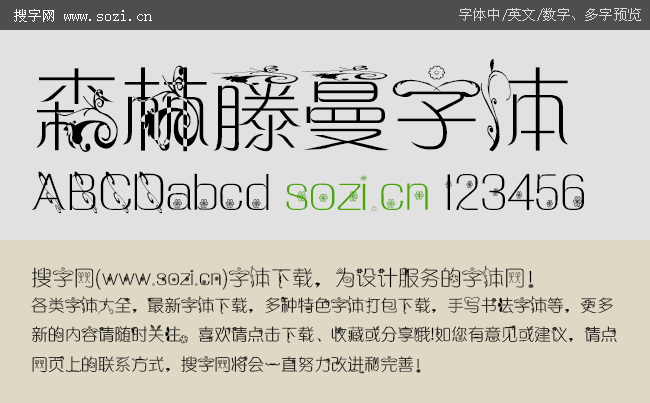
森林藤蔓字體
搜字網(wǎng)給大家提供一款很有趣的手機中文字體下載。修改者給他起名為森林藤蔓字體,這款手機字體是將中倩體字體部分筆畫替換成了漂亮的花紋圖案。中倩體筆劃粗細(xì)對比適中,婉轉(zhuǎn)嫵媚,溫順乖巧,看似平淡無奇,卻能給人以美的感受。 插入花紋后增加了趣味性,是一款非?蓯鄣目ㄍㄗ煮w,特別適合喜歡手機字體個性一些的朋友在手機上安裝使用。